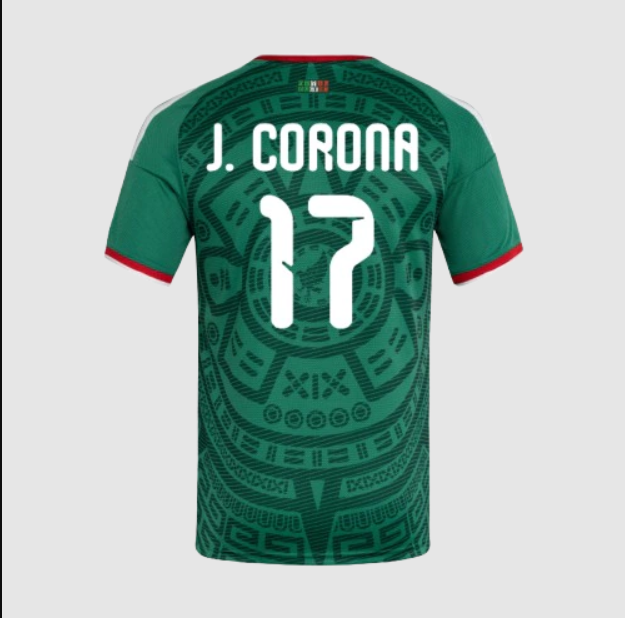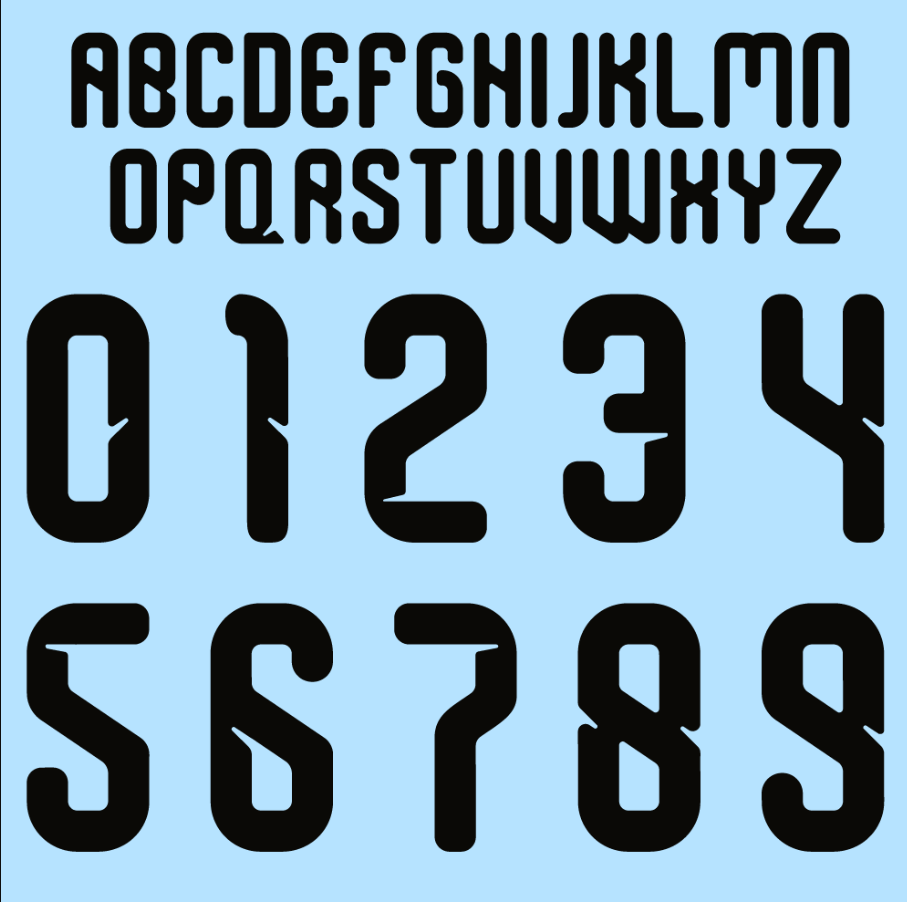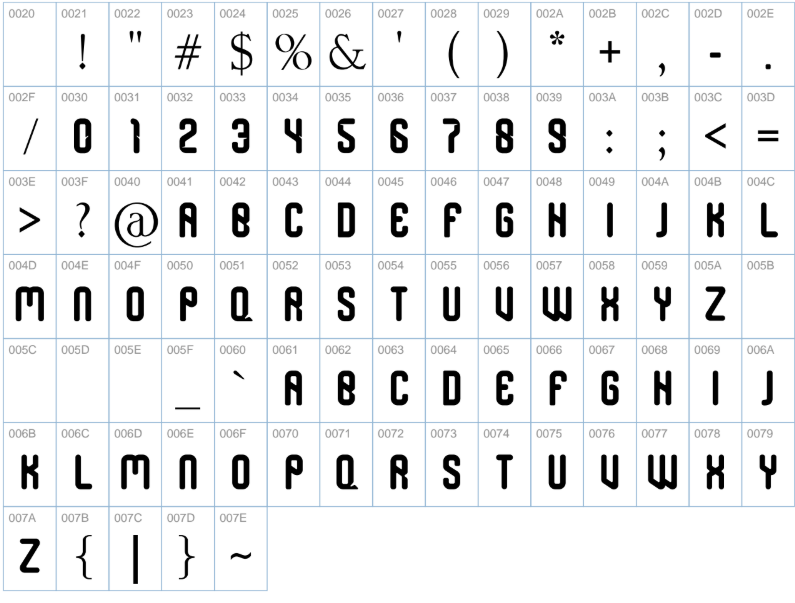
O mundo já está de olho na próxima grande festa do futebol e a Seleção Mexicana será uma das protagonistas como anfitriã. Para o ciclo do Mundial de 2026, a Adidas renovou a identidade visual de “El Tri”, trazendo uma tipografia que mistura modernidade com raízes culturais profundas.
Estilo Visual e Identidade
A tipografia desenvolvida pela Adidas para a Seleção do México neste ciclo de 2024/2026 foge do padrão genérico. Ela apresenta uma construção geométrica sólida, mas com cortes estilizados que remetem à arte pré-hispânica e à arquitetura asteca, uma marca registrada dos uniformes mexicanos.
É uma fonte que transmite força e movimento. Nos uniformes titulares e reservas, os números possuem uma legibilidade excelente, destacando-se tanto nas transmissões 4K quanto no tecido da camisa. É a escolha perfeita para quem busca replicar com fidelidade o visual dos jogadores em campo.